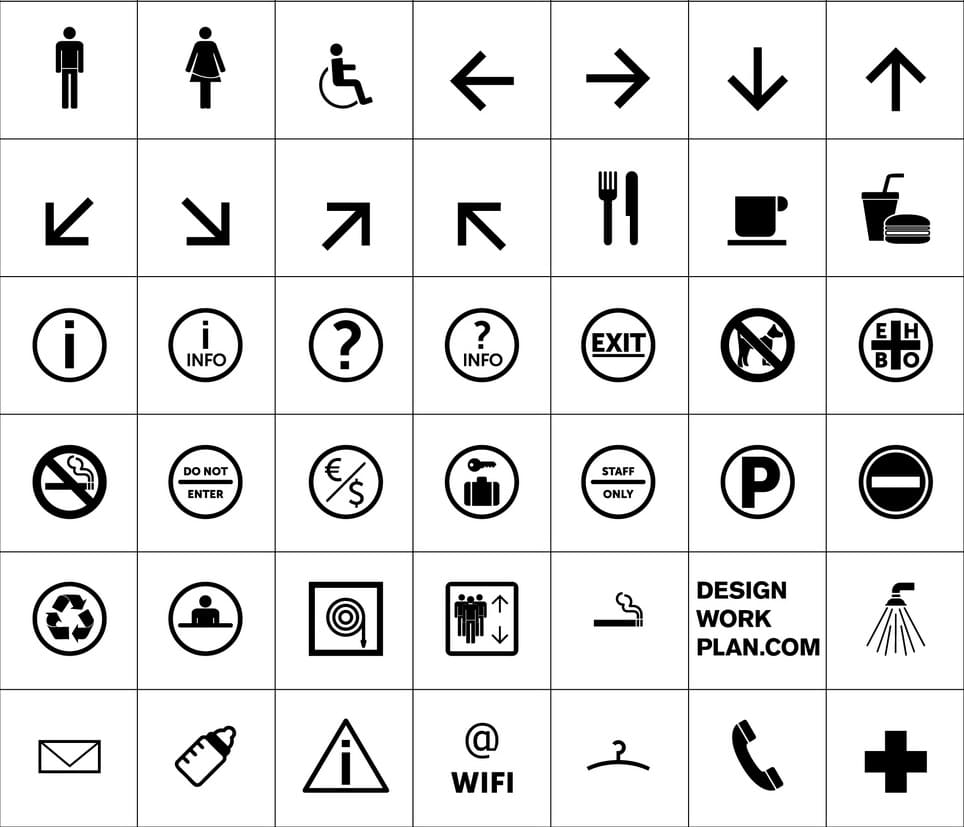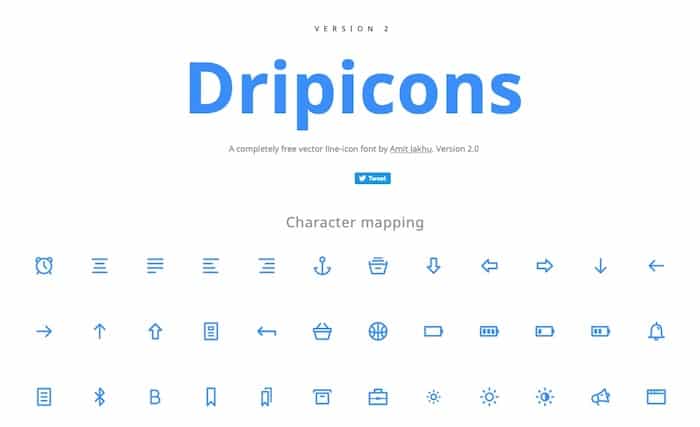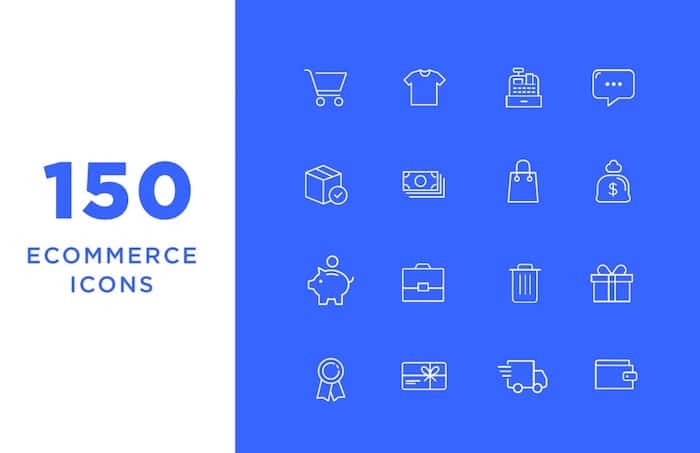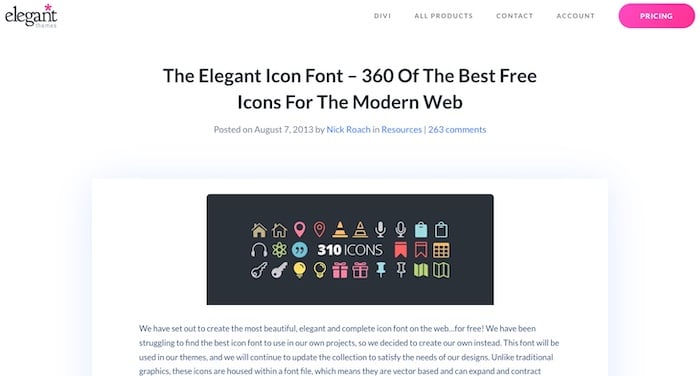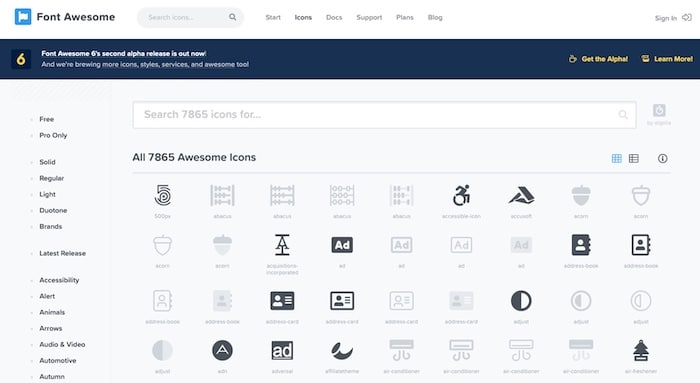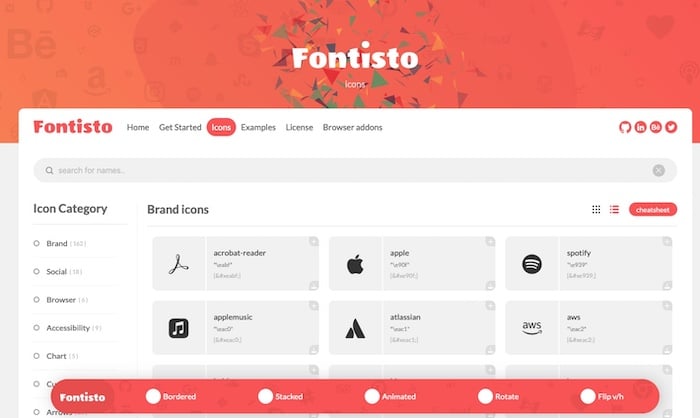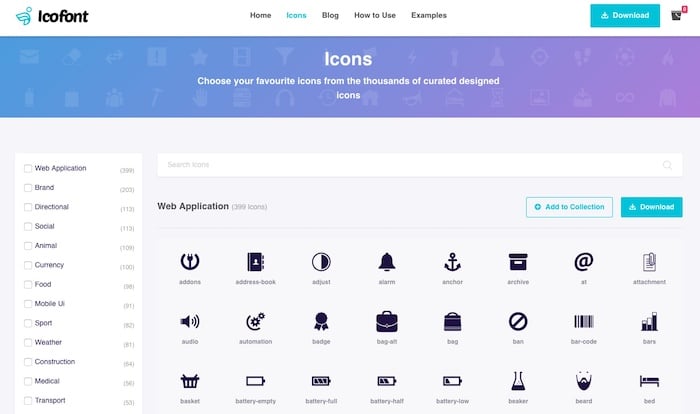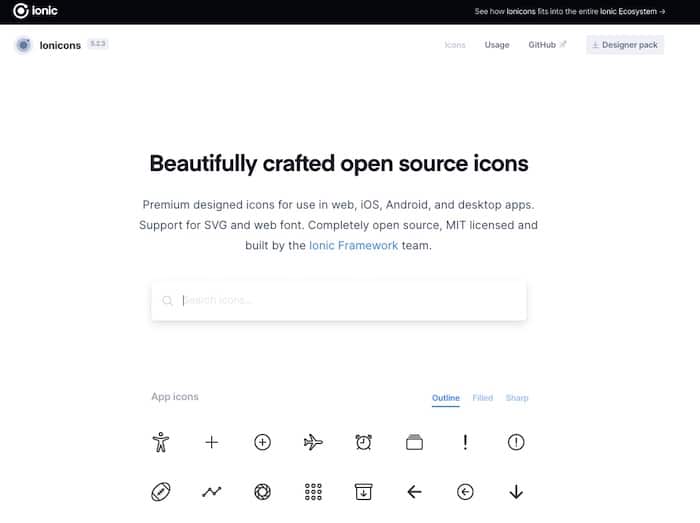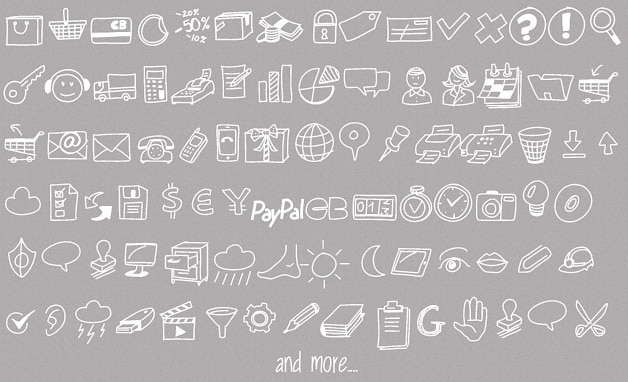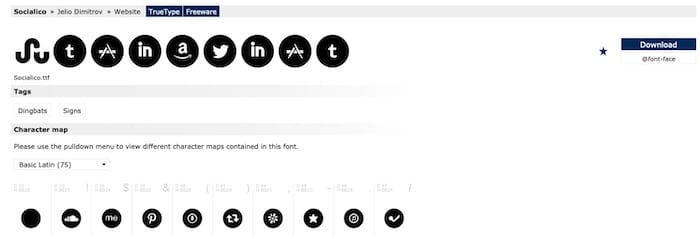
13 icon fonts esthétiques et gratuites pour le web
De nos jours, avoir à disposition de bonnes polices d’icônes est un élément essentiel de tout site web. Elle doit s’adapter au design, y compris dans le cadre d’une conception web responsive ; elle doit être facile à superviser, et on doit facilement pouvoir en faire varier la couleur, la taille.
Toutes les propriétés CSS pour le texte sont applicables aux icon fonts, et c’est bien sûr un avantage majeur.
Cet article recense quelques polices d’icônes populaires, d’autres récemment publiées sur le web.
Ces packs d’icônes comptent parmi les plus populaires, car ils sont bien souvent la seule ressource dont vous aurez besoin : ces polices couvrent tous les domaines et disposent d’une quantité impressionnante d’icônes.
Font Awesome est la reine incontestée des polices d’icônes. Dans une même collection, elle offre plusieurs centaines d’icônes différentes. Bien qu’elle ait été conçue à l’origine pour le framework Bootstrap, Font Awesome fonctionne bien avec tous les autres frameworks. L’hébergement du pack d’icônes est le meilleur moyen de l’utiliser, les plans basés sur la solution Cloud ont des limites d’utilisation.
Icofont est sans doute la police d’icône la plus fournie que vous pouvez télécharger et utiliser gratuitement. Cette police comprend en effet plus de 2100 icônes réparties dans 30 catégories différentes telles que la monnaie, les logos sociaux, les logos de marque, etc. L’un des avantages de ce pack est qu’il est disponible à la fois au format SVG et comme police.
La police Elegant Icon comprend 360 icônes gratuites couvrant une variété d’utilisations. Toutes les icônes sont entièrement libres d’utilisation. Comme son nom l’indique, la police Elegant Icon vient d’Elegant Themes, les créateurs du célèbre thème pour WordPress Divi.
Fontisto est une autre grande police d’icônes gratuite qui présente un ensemble d’icônes modernes et élégantes classées dans plusieurs catégories. Les icônes (entièrement modulables) s’affichent parfaitement sur les écrans Retina. Elle est entièrement gratuite, même pour les projets commerciaux.
Ionicons est un autre ensemble d’icônes présentant cette fois un trait simple et minimaliste. Cette police est spécialement conçue pour la conception d’interfaces utilisateur web et mobiles et elle est compatible avec les plateformes iOS et Android. Elle comporte un total impressionnant de plus de 1000 icônes. Elle est sous licence open-source.
Dripicons est une collection d’icônes présentant également des motifs lisses et minimalistes. Les icônes permettent des mises en page modernes, qui conviennent à la fois aux interfaces utilisateur web et mobiles. Leur utilisation est gratuite même pour les projets commerciaux.
Typicons comprend plus de 330 modèles d’icônes différents, classés dans plusieurs catégories. C’est un ensemble d’icônes légères et simples, qui conviendront à la fois sur le web et sur les interfaces utilisateur des applications natives.
Vous avez besoin d’un ensemble d’icônes que vous pourrez utiliser avec l’API Google Map ? Si oui, les Map Icons sont faites pour vous. Très utiles pour afficher des lieux de manière plus esthétique.